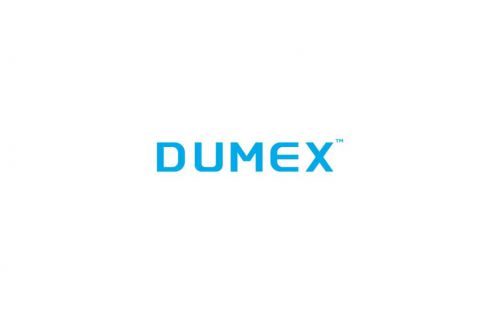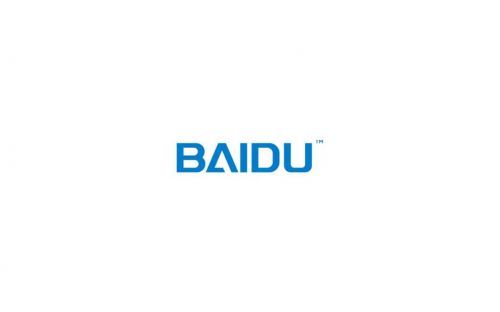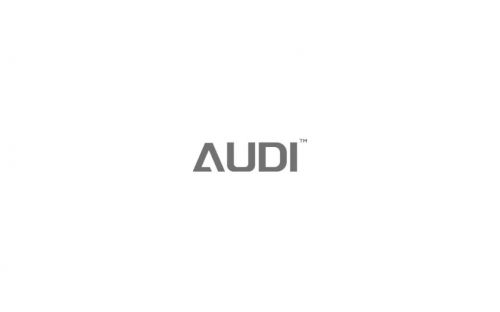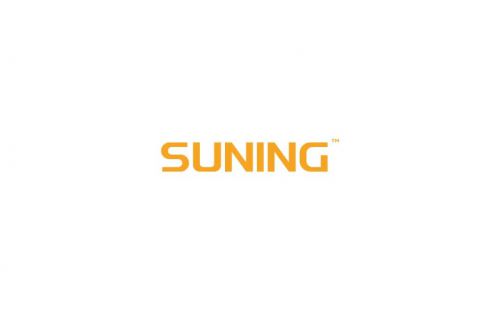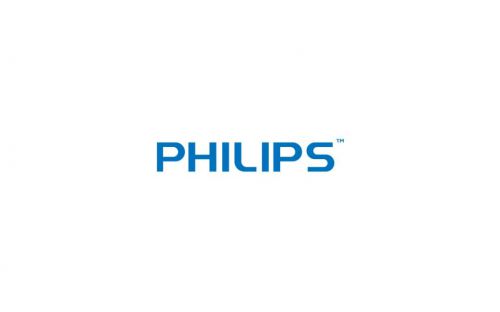
字体圈欣意LOGO体
字体圈欣意LOGO体是一款专为英文(拉丁)设计的Display(展示)类字体,以简约有趣的风格著称,兼具实用性与设计巧思。 字体圈欣意LOGO体字形方正稳重,重心居中平衡,中宫宽博的设计让字符舒展大气,视觉上兼具稳定感与呼吸感。方头笔画利落干脆,搭配巧妙的断开设计,打破常规笔画连接逻辑,局部装饰元素的加入则为字体注入活泼趣味,让简约基调中透出灵动个性。 字重饱满粗壮,笔画粗细均匀,线条张力十足,视觉冲击力强,尤其适合品牌LOGO、标题设计、包装标识等展示场景,能轻松驾驭各类创意主题,快速抓住受众目光。 作为免费商用字体,字体圈欣意LOGO体覆盖常规字符集,授权范围宽松,无论是商业项目还是个人创作,都能无忧使用。字体圈欣意LOGO体以“简约为骨、趣味为魂”,是追求个性与实用平衡的设计师的理想选择,为设计作品增添独特魅力。